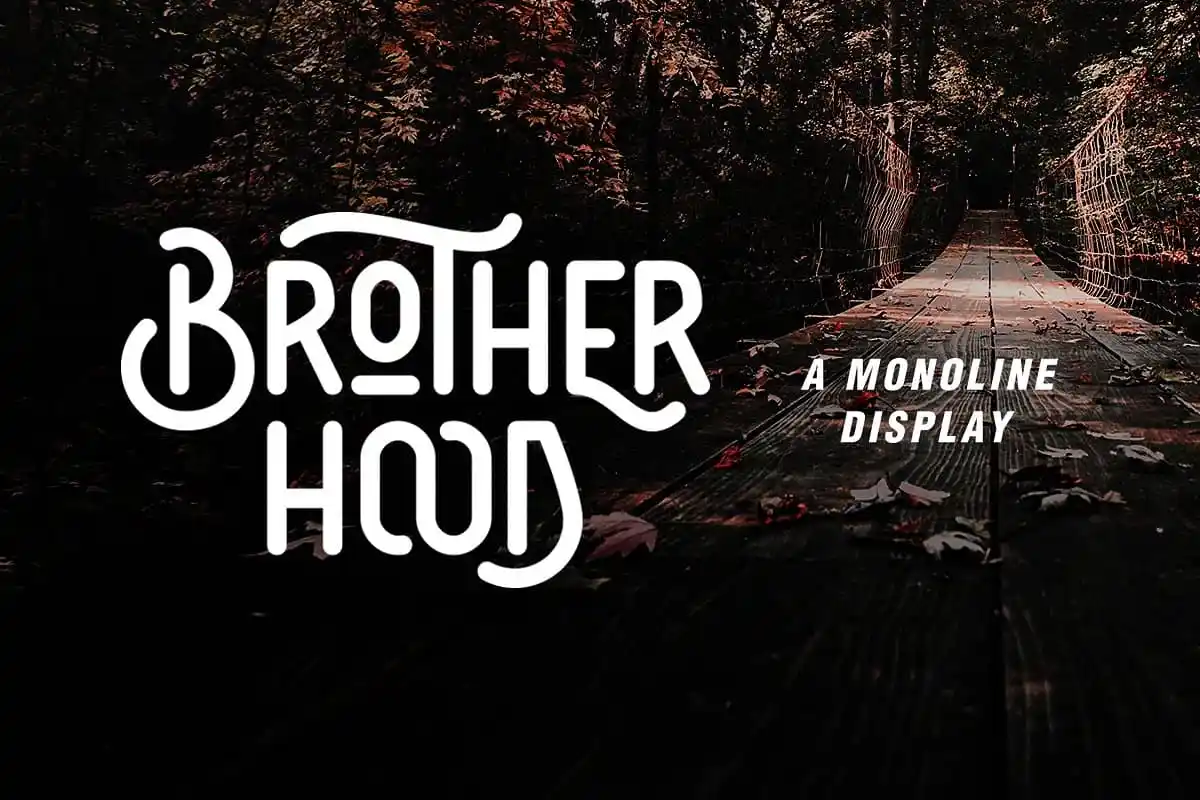
Brotherhood Display Font – Fonte Grátis
Brotherhood Display Font
Através do designer Hamilton, a fonte Brotherhood Display Font oferece uma experiência visual única que vai deixar seu design brilhar. Este é um tipo vintage para uso exibicional, onde cada letra foi cuidadosamente criada para garantir que sua mensagem seja apresentada de maneira impressionante e elegante. Através de sua capacidade monoline em sans-serif, a fonte Brotherhood é perfeita para uma ampla variedade de projetos como logos, letras, citações, roupas, moda, fotografia e até mesmo marcas d’água. Além disso, o tipo possui vários alternativos para caracteres e ligaturas que ajudam você a criar designs estilizados, enquanto alternativas de caracteres podem melhorar ainda mais seu design exibicional. Com um cuidado meticuloso em cada gílico, Hamilton criou uma fonte que é uma verdadeira arte. Não importa o projeto ou plataforma em que você escolha usá-la, Brotherhood Display Font se destaca como uma opção excepcional para qualquer designer que valoriza a qualidade visual e deseja transformar seus designs em algo realmente especial.